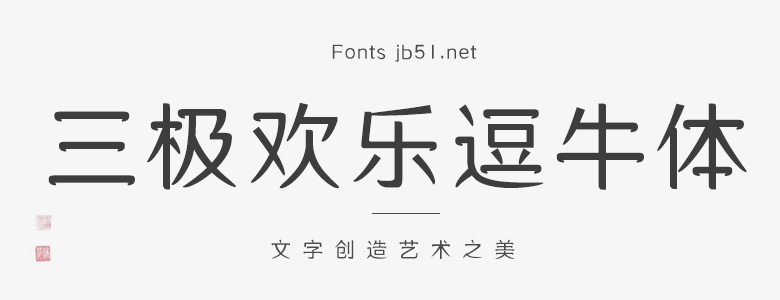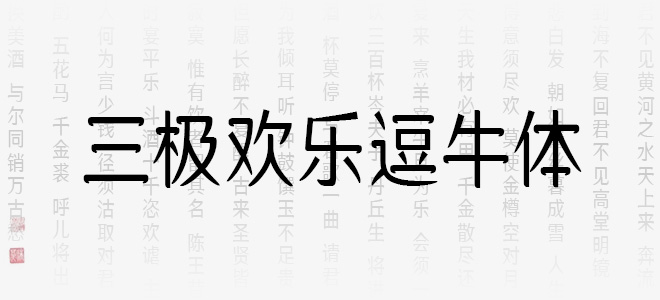
三極歡樂(lè)逗牛體是一款新穎的字體,大部分的筆畫(huà)采用了殘缺的牛角樣式的風(fēng)格,給人一種壯碩、強(qiáng)悍的精神氣息。適用于各類品牌廣告、包裝設(shè)計(jì),以及傳統(tǒng)印刷媒介的標(biāo)題與正文排版。歡迎喜歡三極歡樂(lè)逗牛體的朋友前來(lái)下載使用。
三極歡樂(lè)逗牛體